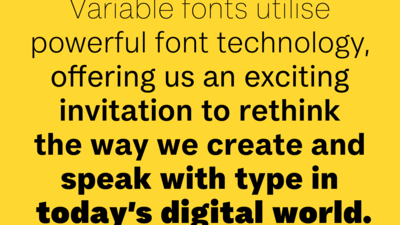
L’évolution de la typographie avec les polices variables.
“ Une police variable est une police unique qui agit comme plusieurs : toutes les variations (chasse, graisse, inclinaison et même les italiques) peuvent être contenues dans un seul fichier de police, hautement efficace et compressible. ”
Grâce à l’émergence des polices variables, il n’est plus nécessaire aujourd’hui de sacrifier le design des sites Web au profit de la vitesse des pages. Jason Pamental explore les avantages des polices variables et la manière dont elles peuvent transformer la conception de sites Web.
Depuis des siècles, la typographie est un moyen « d’entendre » ce que nous lisons. Tout le monde s’accorde à dire qu’il s’agit aussi d’un élément central de l’image de marque, de l’expression, de la gamme vocale. Une grande typographie influence la compréhension, l’humeur et le sens de nombreuses façons, et constitue une part essentielle du design.
Malheureusement, depuis l’avènement du Web, de nombreuses années se sont écoulées sans que l’on puisse appliquer au contenu en ligne les principes les plus élémentaires du design typographique. Grâce à la possibilité d’utiliser de vraies polices et des fonctions OpenType (ligatures, jeux de chiffres spécifiques, fractions et crénage véritable), le paysage typographique s’est considérablement amélioré.
Mais la visualisation du contenu sur le Web est une réalité qui impose toujours la vitesse comme l’aspect le plus critique de la conception – souvent, la « gamme vocale » typographique est troquée contre la vitesse de la page. On privilégie des graisses de police moins lourdes quitte à amoindrir la fidélité à l’image et à la voix de la marque.
De la multitude, à l’unité : changement de paradigme
L’apparition des polices variables modifie en profondeur cette dynamique. Comme le décrit John Hudson, une police variable est une police unique qui agit comme plusieurs : toutes les variations (chasse, graisse, inclinaison et même les italiques) peuvent être contenues dans un seul et même fichier de police, hautement efficace et compressible.
De plus, le format (qui fait techniquement partie de la spécification OpenType 1.8) est entièrement extensible. Le designer typographique a un contrôle total sur les axes utilisés, leurs portées et même la définition de nouveaux axes. Actuellement, il existe 5 axes « pré-enregistrés » (chasse, graisse, oblique, italiques et taille optique). Mais le designer peut modifier n’importe quel axe et lui apporter la variation désirée. Parmi les exemples, on peut noter la hauteur des ascendantes et des descendantes, la graduation du texte et même la forme des empattements.
“ Une police variable est une police unique qui agit comme plusieurs : toutes les variations (chasse, graisse, inclinaison et même les italiques) peuvent être contenues dans un seul fichier de police, hautement efficace et compressible. ”
En supprimant la barrière de la performance, nous ouvrons la porte à des designs plus intéressants et dynamiques. La capacité d’exprimer la voix véritable d’une marque est nettement supérieure. Tout cela, en restant fidèle à la police de caractère elle-même : seuls les axes exposés par le designer de la création typographique peuvent varier. Aucune distorsion artificielle n’est autorisée.
Métamorphose de la conception Web
Bien que la technologie poursuit sa phase de maturation et que les designers typographiques cherchent à gagner en agilité avec cette nouvelle méthode de travail, les perspectives pour concevoir sur le Web sont révolutionnaires. Le scénario typique serait de se limiter à un total de 3 à 5 polices différentes pour représenter chaque aspect du langage design et de la voix d’un site – y compris les permutations pour le corps du texte et les titres.
Dans sa mise en œuvre la plus simple, les polices variables nous donneraient la liberté d’utiliser différentes graisses pour chaque niveau de titre – ce qui renforcerait considérablement leur clarté et leur lisibilité.
Pour les titres ou pour les affichages qui sont denses en données, on pourrait également utiliser des largeurs de caractères légèrement plus étroites. En fait, l’ensemble du système typographique pourrait être conçu de manière proportionnelle : la graisse et la chasse pourraient devenir des multiplicateurs des paramètres standard du corps du texte. Ces aspects s’adapteraient ainsi facilement au texte, si ses paramètres changent en fonction de la taille de l’écran ou des préférences de l’utilisateur. Tout cela s’accompagnerait d’une augmentation des performances, en raison de la diminution du nombre de requêtes HTTP (moins de fichiers de police) et d’une économie globale de données à télécharger (bien que cela varie selon la police et la compression utilisées).
Mais si ces libertés nous permettent d’être plus expressifs, certaines des capacités les plus intéressantes contribueront à transformer l’expérience de lecture elle-même.
Réinventer la lecture sur écran
L’un des plus grands défis dans la création d’une bonne expérience de lecture, c’est la recherche de finesse dans les proportions et les petits détails. Associer les CSS modernes et les fonctionnalités et variations OpenType présente une combinaison puissante. ll est possible de définir des caractéristiques : ligatures et césure en fonction de la langue, activer ou désactiver la césure selon la taille de l’écran… Sur les écrans les plus petits, la chasse des caractères peut aussi être ajustée pour faire tenir plus de caractères par ligne, sans réduire la taille de la police. Ces éléments améliorent considérablement la fluidité et le confort de lecture.
Expérimenter les polices variables
Une démo de FF Meta Variable est disponible gratuitement au format police de bureau et police Web. À découvrir et télécharger dès maintenant pour expérimenter pleinement les polices variables et la manière dont elles redéfinissent la conception pour le Web.